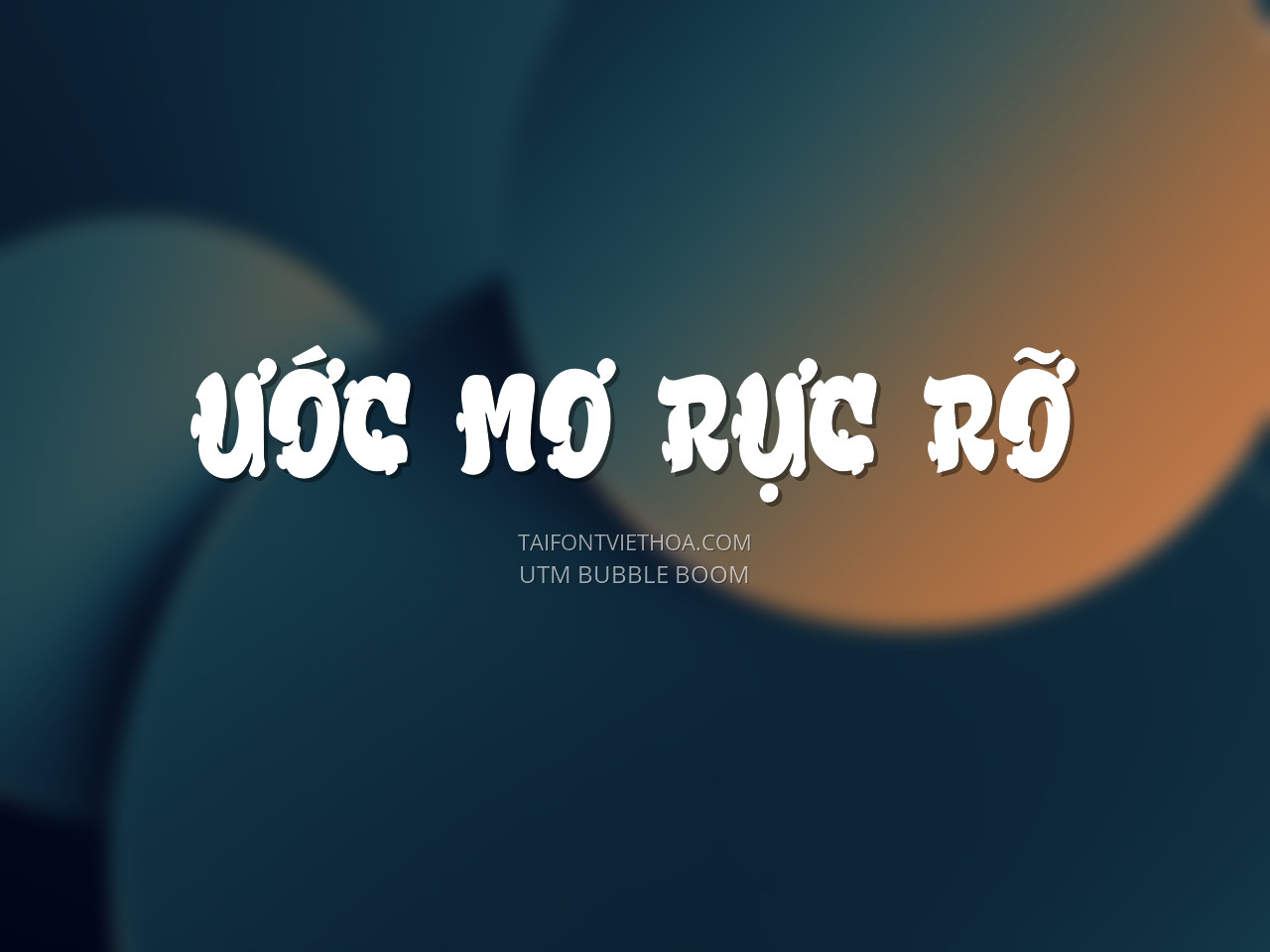
Font việt hóa UTM Bubble Boom
Giới thiệu về font UTM Bubble Boom
UTM Bubble Boom là phiên bản Việt hóa của font Bubble Boom – một kiểu chữ display độc đáo và năng động, được thiết kế với phong cách vui nhộn và trẻ trung. Font gốc nổi bật với các nét chữ tròn trịa, đậm nét và có hình khối mạnh mẽ, mang lại sự thu hút và ấn tượng ngay từ cái nhìn đầu tiên. Phiên bản Việt hóa đã được hoàn thiện để hỗ trợ đầy đủ tiếng Việt cùng hơn 100 ngôn ngữ khác, giúp mở rộng khả năng sử dụng trong các dự án thiết kế sáng tạo và giải trí.
Font UTM Bubble Boom được taifontviethoa.com sưu tầm và chọn lọc kỹ càng nhằm phục vụ cộng đồng thiết kế Việt Nam. Phiên bản Việt hóa này giữ nguyên phong cách vui tươi và độc đáo của bản gốc, đồng thời tối ưu khả năng hiển thị tiếng Việt, rất phù hợp cho các dự án quảng cáo, poster và truyền thông giải trí.
Đặc điểm thiết kế và ứng dụng của UTM Bubble Boom
UTM Bubble Boom sở hữu cấu trúc display với các nét chữ tròn trịa, dày dặn và đồng đều. Font có thiết kế vui nhộn, bắt mắt và dễ nhận diện, rất phù hợp cho tiêu đề, logo và các thiết kế cần sự khác biệt. Font còn được tối ưu để đảm bảo tính dễ đọc trên nhiều kích thước và môi trường sử dụng khác nhau.
Font phù hợp sử dụng trong thiết kế poster, bảng hiệu, quảng cáo, nhận diện thương hiệu và các dự án truyền thông sáng tạo. Các ngành nghề phù hợp gồm: giải trí, quảng cáo, thời trang, sự kiện và truyền thông đa phương tiện.